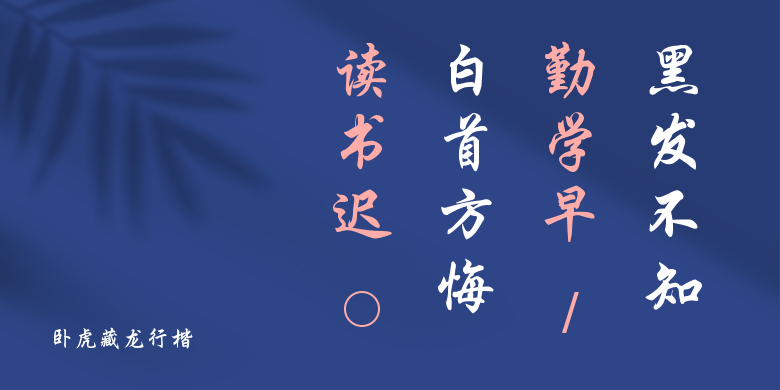
卧虎藏龙行楷
卧虎藏龙行楷,这款字体结构工整、笔画清晰,兼顾美观与易读性,适用于标题、正文、海报、包装、LOGO 等多种场景。字形优雅稳定,风格百搭耐看,适配日常排版与创意设计,让文字呈现更舒适、更具质感。卧虎藏龙行楷一笔一画,皆是细节,以均衡的比例、流畅的线条打造舒适视觉体验,字形端正大气,风格简约现代。无论是商业设计、品牌宣传还是日常排版,都能轻松驾驭,让文字更有格调与力量。卧虎藏龙行楷字体下载。